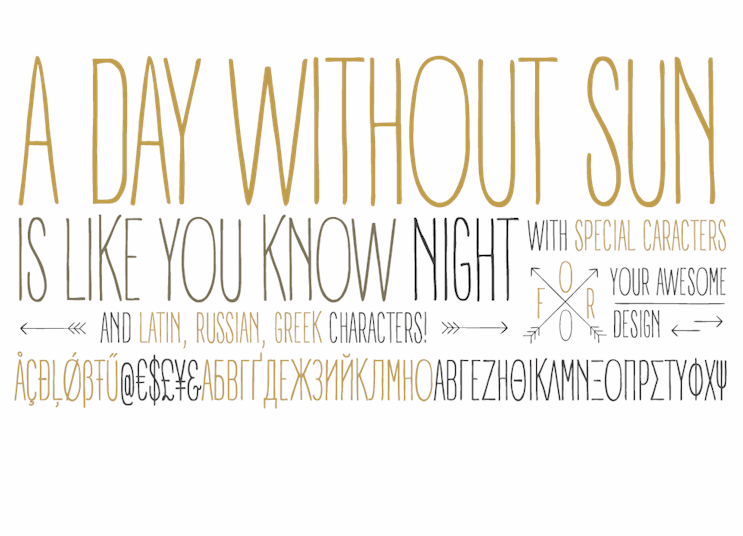
A DAY WITHOUT SUN Font
A DAY WITHOUT SUN é uma nova adição à família de fontes Panforte criada por Zetafonts, designer conhecido por seus trabalhos únicos e originais. Esta fonte foi inspirada na versão ultra-condensada de Panforte, projetada pelos talentosos designers Cosimo Lorenzo Pancini e Debora Manetti. Com uma aparência retrô elegante e textura manufaturada, esta fonte é perfeitamente adequada para criar textos com um toque vintage que remete aos menus de restaurantes de alta qualidade. Embora seja uma versão ultra-condensada, A DAY WITHOUT SUN mantém seu estilo único mesmo a medida mais baixa. Suas linhas são diretas e simples, criando um efeito de escrita real. O designer incorporou características que tornam a fonte única, como números antigo e ligaturas, garantindo um visual autêntico. Com suporte para cerca de quarenta línguas usando o alfabeto latino, a font também inclui diacríticos selecionados cuidadosamente e caracteres gregos e cirílicos. O grande encanto desta font é sua natureza manufaturada e “manuscrita”, que aparece em tamanhos médios e altos, mas não interferem com seu uso no texto. Este tipo de fonte open type é perfeito para aqueles que querem adicionar um toque único a seus projetos digitais sem comprometer sua funcionalidade. Visite o site do Zetafonts (http://www.zetafonts.com/) para explorar a família completa de Panforte e descubra todas as suas possibilidades, incluindo seu lado grego e cirílico.